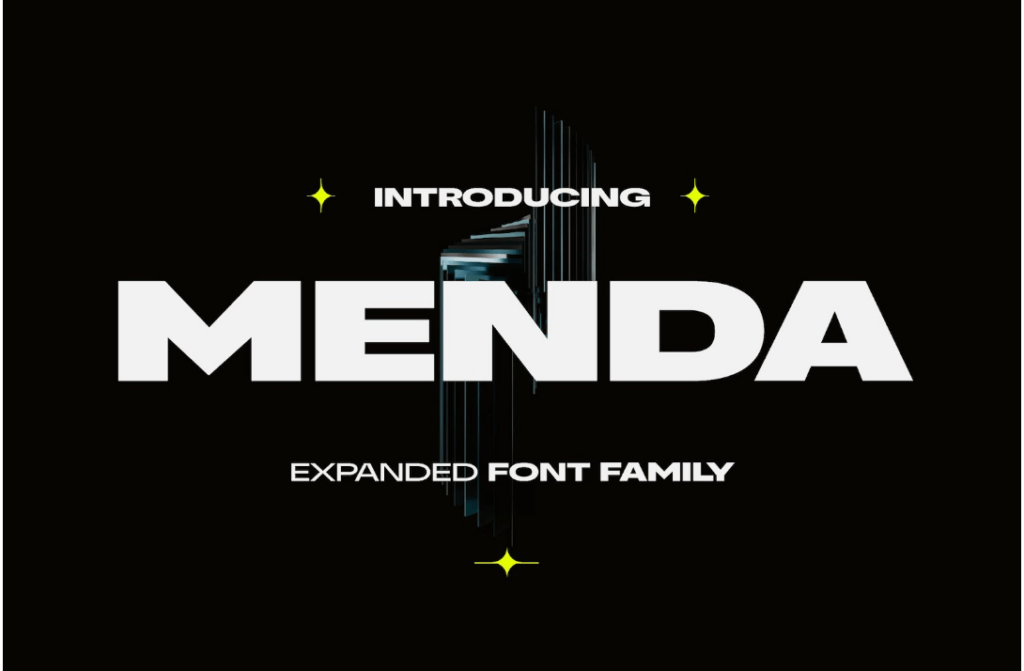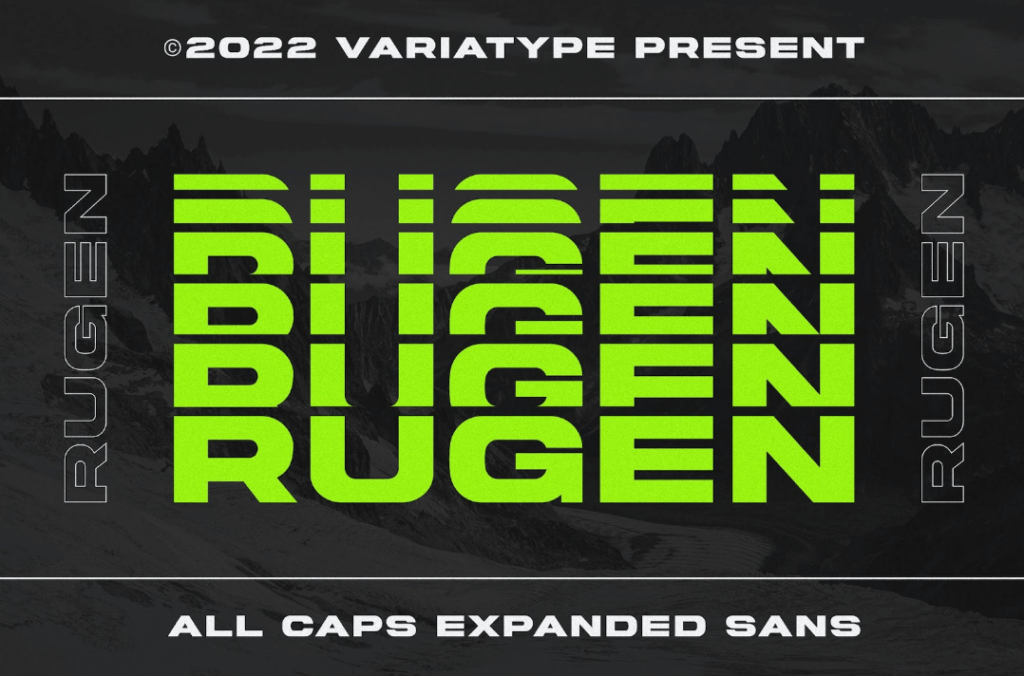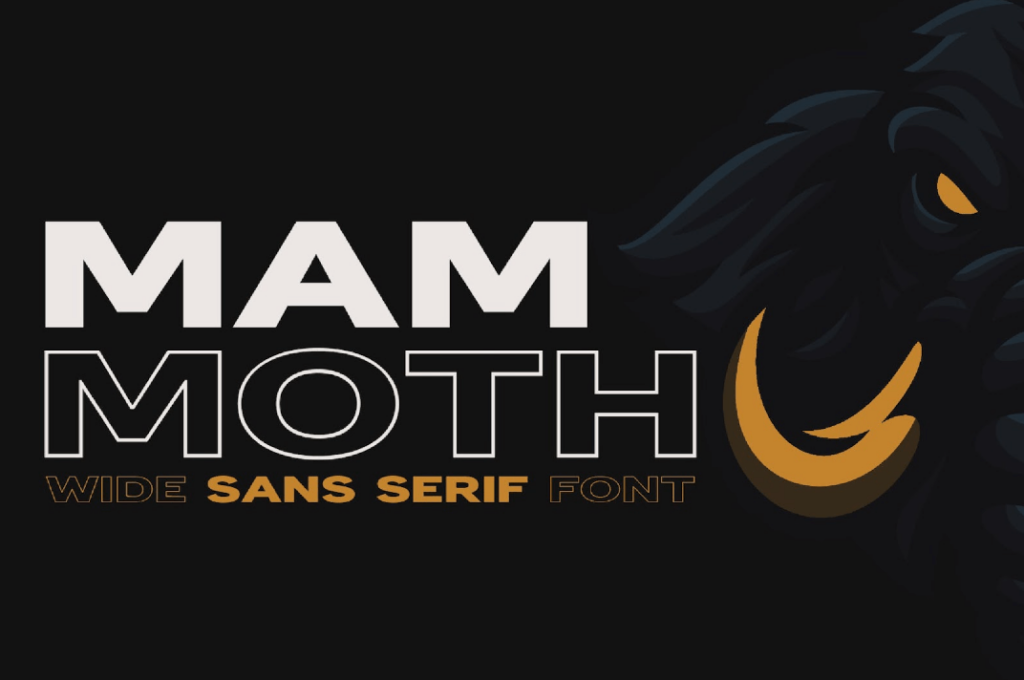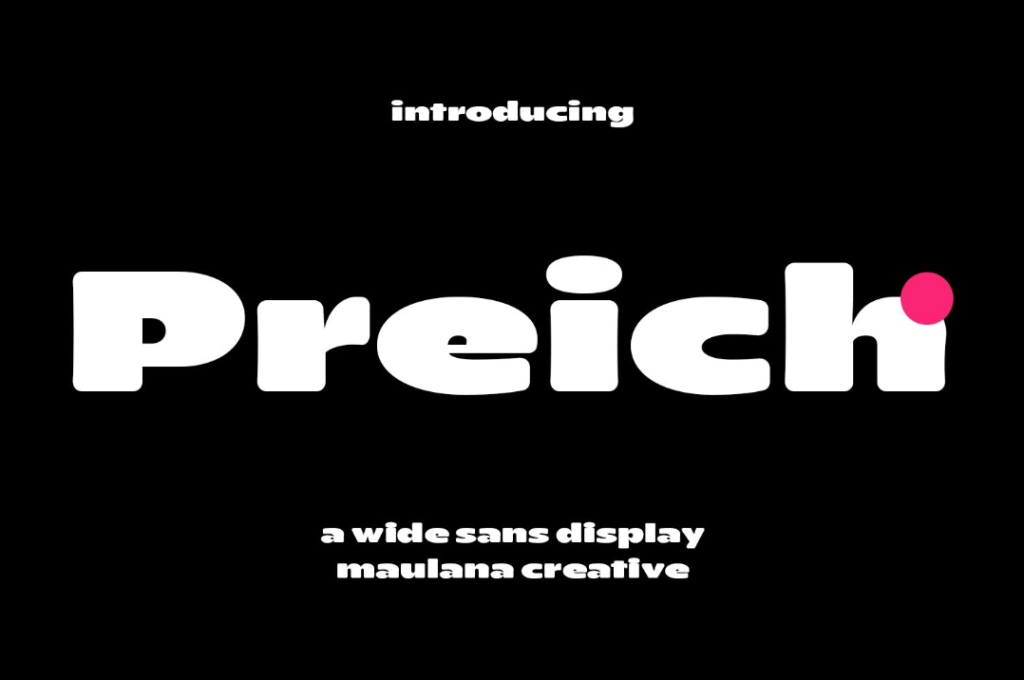
Растянутые или широкие шрифты помогут сделать ваш дизайн-проект более ярким, привлекательным и интересным. Широкие символы, расширенные буквы и большие пробелы между элементами придадут строгость и смелость вашему дизайну.
Menda — это современное семейство шрифтов, в котором сочетаются геометрические формы и жирные линии. У букв шрифта четко очерченные линии и изгибы, которые помогают обеспечить читаемость даже при больших размерах. Поэтому этот шрифт идеально подойдет для заголовков, плакатов и брендинга.
Rugen — это элегантный шрифт без засечек в современном стиле. Идеально подходит для различных проектов брендинга и предлагает уникальные функции, такие как акценты, кернинг и альтернативы. Шрифт также поддерживает 66 языков. Пакет включает в себя различные форматы шрифтов, такие как OTF, TTF, WOFF и WOFF2.
Mammoth — это смелый широкий шрифт без засечек, который может придать новую энергию вашим проектам. Современная и смелая эстетика этого шрифта делает его универсальным выбором для множества проектов — от логотипов до веб-дизайна.
Preich — это широкий шрифт без засечек, который идеально соблюдает баланс между игривостью и структурой. Он включает в себя тяжелые штрихи, захватывающие лигатуры и альтернативы. Preich поддерживает более 100 языков. Он идеально подойдет для логотипов, публикаций в социальных сетях, а также заголовков веб-сайтов.